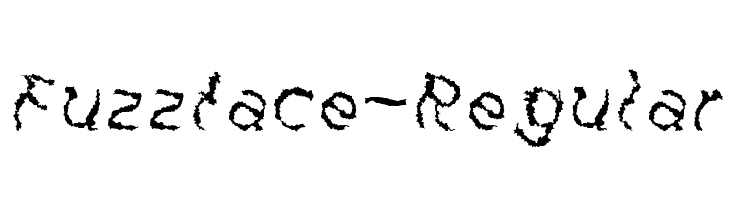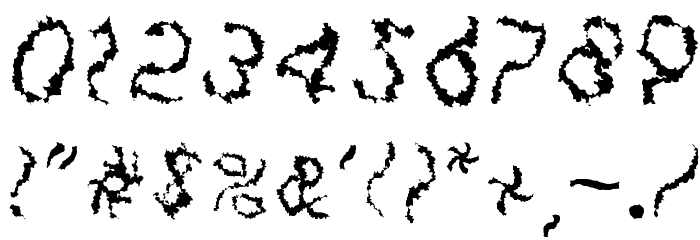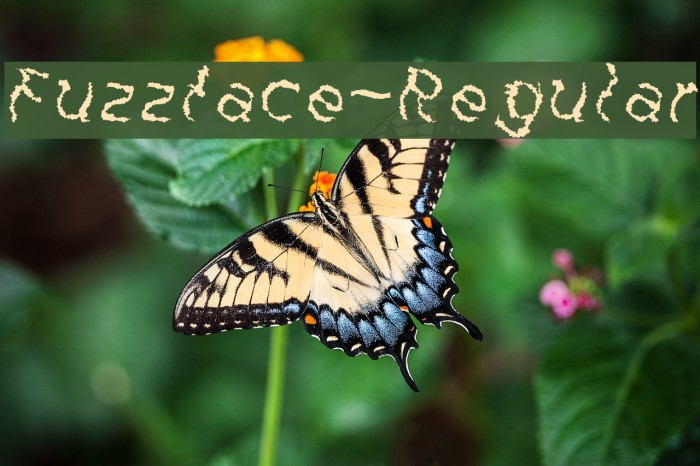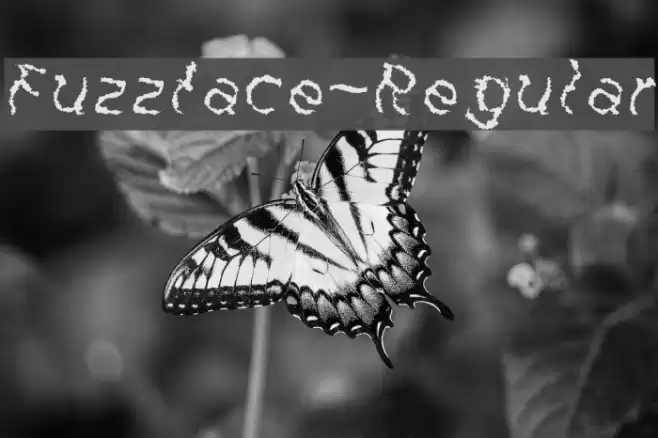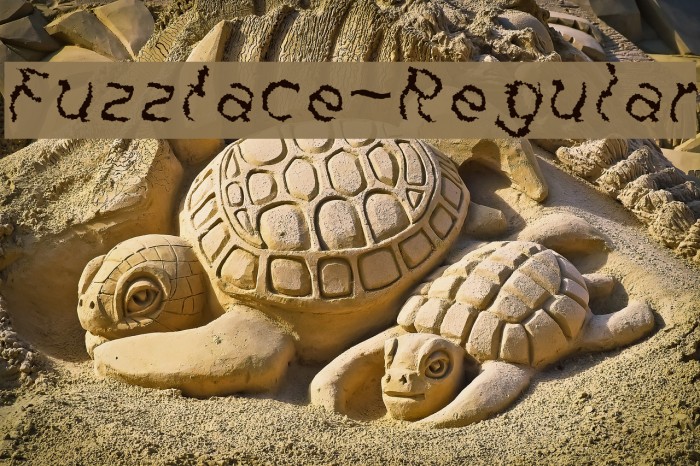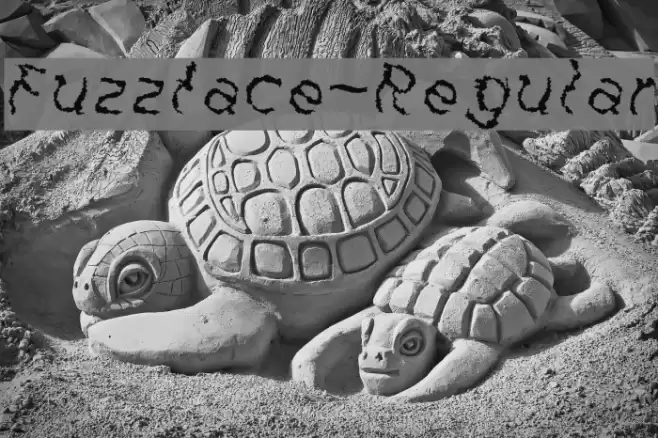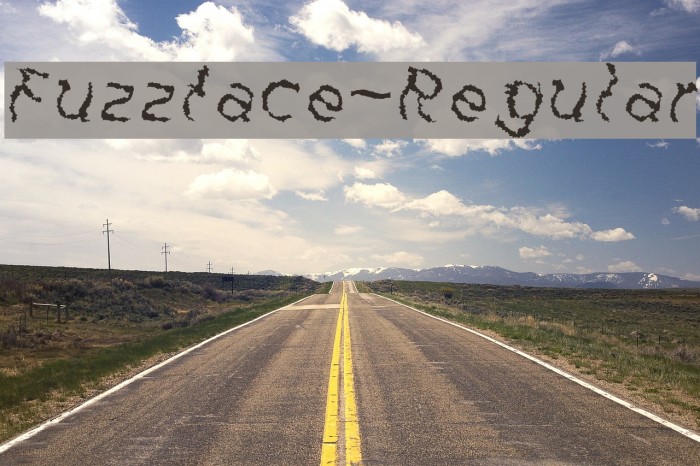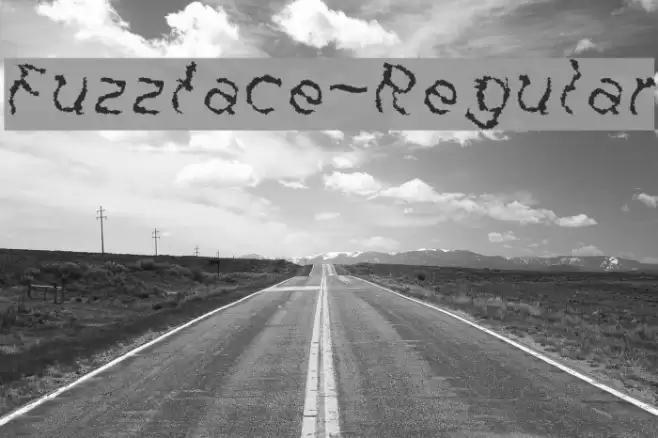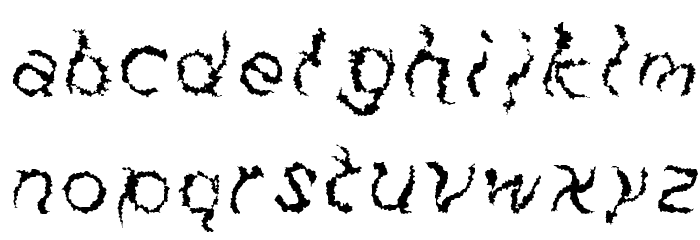
Fuzzface-Regular Font
| Caso de uso | Logos, Posters, Creative Branding |
| Projetos propostos | Ideal for artistic projects, album covers, posters, and creative branding that seeks to convey a sense of nature or dynamism. |